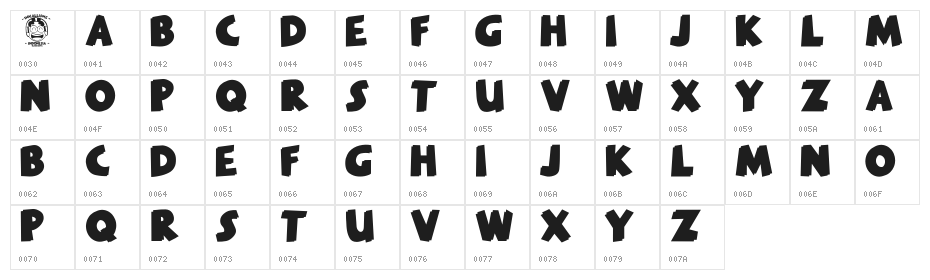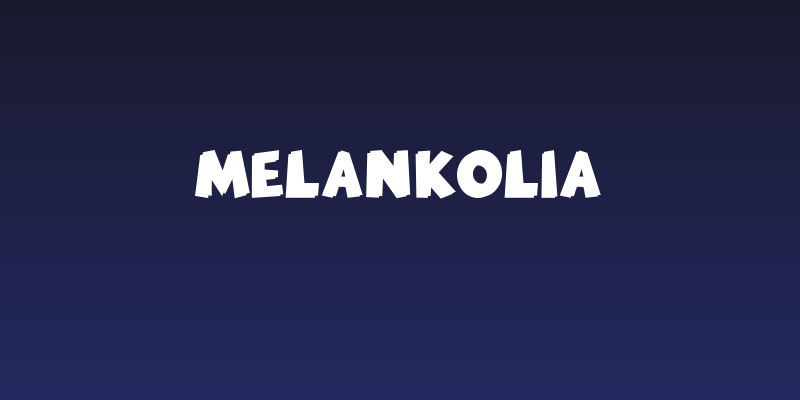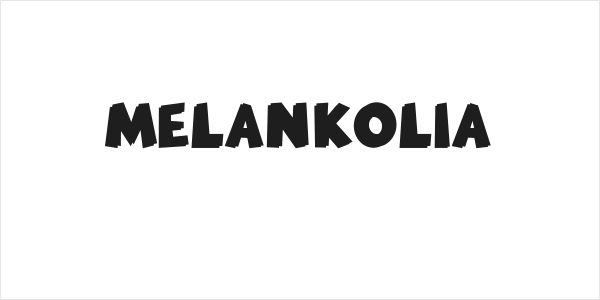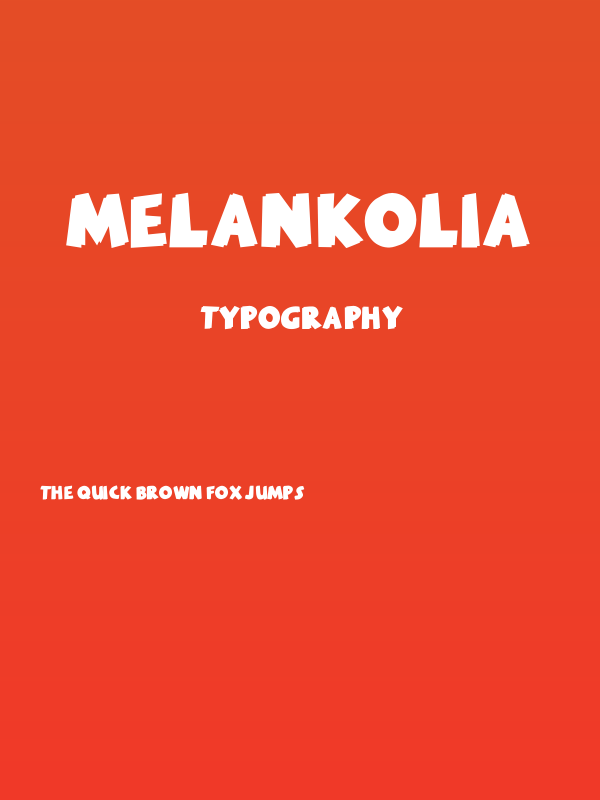
MELANKOLIA Font
| おすすめプロジェクト | This font is perfect for children's books, playful branding, casual invitations, and any project that requires a friendly and approachable typeface. |